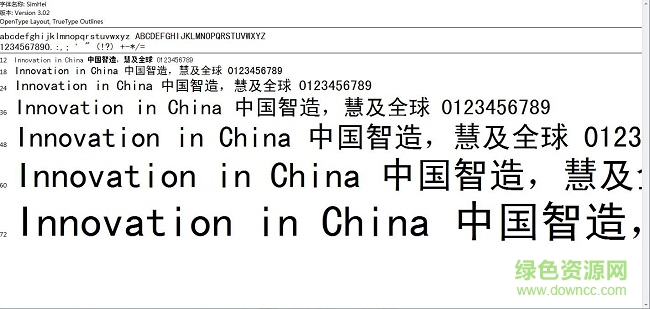
simhei bold字體是一款粗體的黑體字體,筆劃粗壯有力,不適合用在雜志、PPT、書(shū)刊等的正文排版中,一般用于標(biāo)題或海報(bào)封面,有需要者快來(lái)下載收藏吧!
黑體字的橫豎筆畫(huà)的粗細(xì)要相對(duì)一直,“人工設(shè)計(jì)”的效果也更強(qiáng),常被用于作為“力量較強(qiáng)的效果”和“時(shí)尚的效果”的處理!
“黑體”往往指稱的都是活字印刷的黑體。隨著時(shí)代的發(fā)展,“筆畫(huà)粗”已經(jīng)不再適用于描述黑體字了,因?yàn)閺?0 世紀(jì)80 年代起,細(xì)黑體開(kāi)始大量出現(xiàn)并被應(yīng)用到正文領(lǐng)域,改變了印刷黑體單一的品種結(jié)構(gòu),也使得原先的定義變得局限。